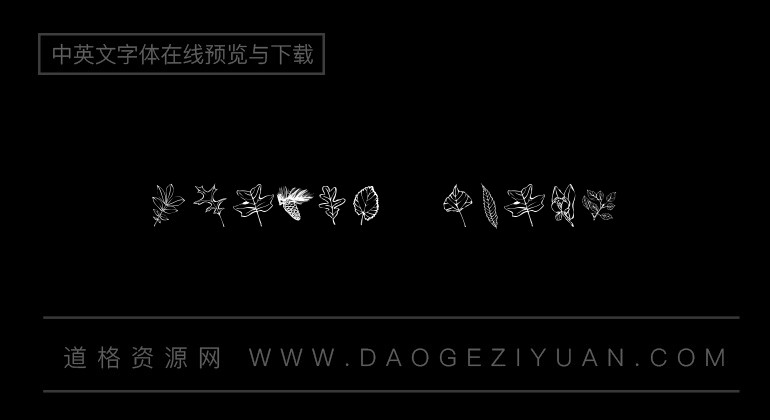
Flower Icons
Flower Icons 字体是一种包含了多种花朵图标的字体,可用于在设计、排版等领域中添加装饰性的图形元素。该字体由一系列花朵图标、叶子、枝干、花瓣和其他植物元素组成,可以用于创建花卉主题的设计。 使用 Flower Icons 字体可以让设计更加生动有趣,增加自然元素的艺术感和浪漫氛围。为了使用 Flower Icons 字体,你需要在电脑上安装相应的字体文件,然后在设计软件中选择该字体,并选择想要使用的花卉图标进行排版设计。 总的来说,Flower Icons 字体是一种实用且美观的字体,适用于多种场合,如海报设计、卡片制作、网站排版等。
Flower Icons是一款非常不错的手写艺术字体,具有很好的视觉感,适合于文化类的宣传设计、商业类品牌的广告和产品包装设计以及个性化文字排版等较多场景。